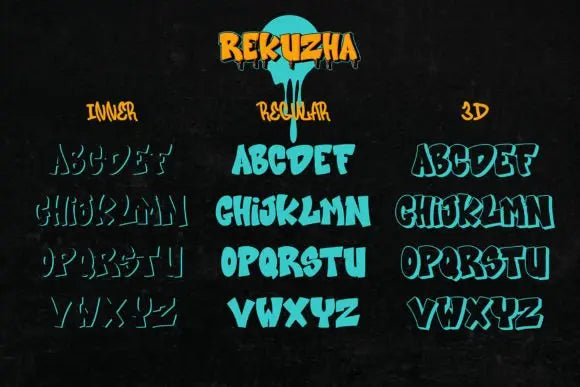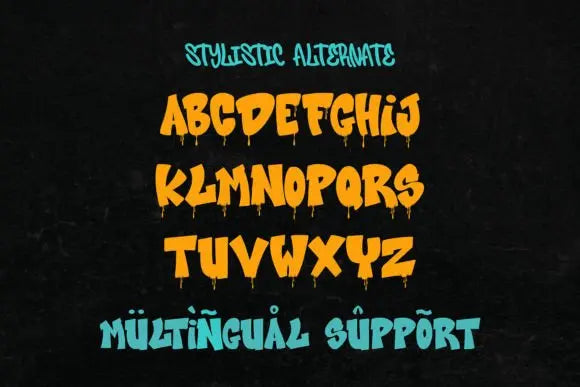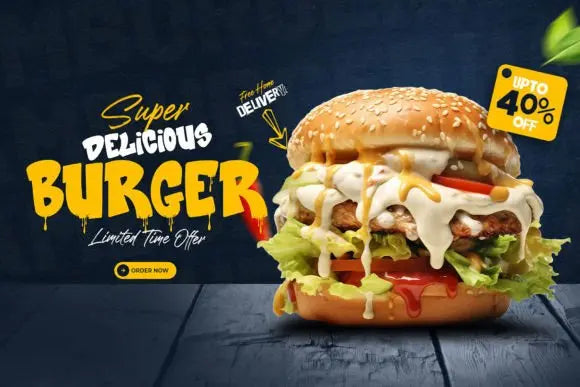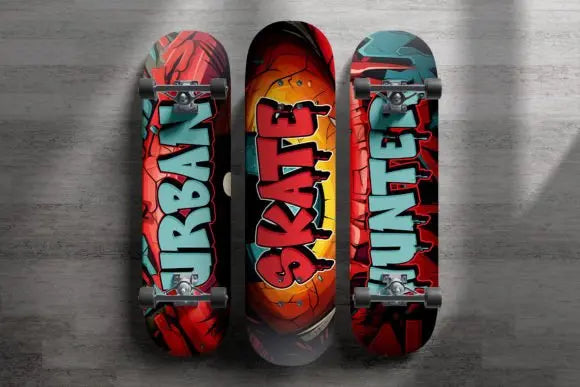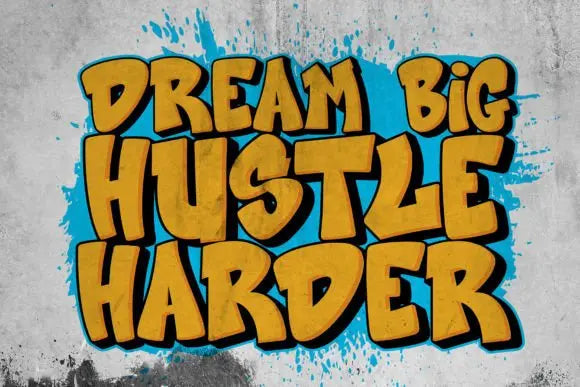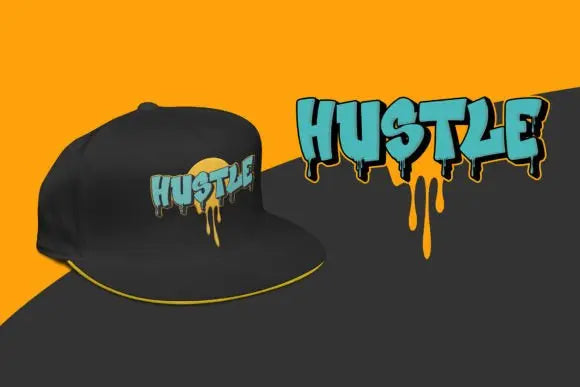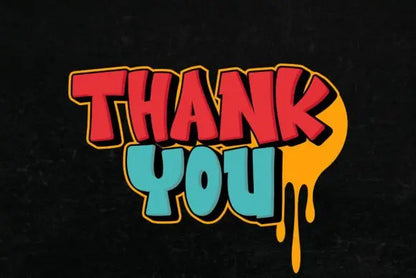
Fuente Rekuzha
Sumérgete en un mundo de audacia, intensidad y creatividad con "Rekuzha", una fuente de graffiti en capas en 3D. Esta fuente, que exhibe formas de letras audaces y enérgicas, está registrada con trazos gruesos y significativos que generan un impacto visual indomable.
El aspecto en capas de “Rekuzha” es el corazón de la aventura: experimenta combinando diferentes estilos, liberando tu espíritu innovador y forjando profundidad en tus diseños. Sus personajes robustos y su composición escalonada hacen de “Rekuzha” la opción perfecta para proyectos que exigen una tipografía llamativa y llamativa: piense en carteles, titulares o diseños centrados en lo urbano.
La tridimensionalidad de esta fuente logra profundidad y compromiso visual, lo que convierte a "Rekuzha" en una opción versátil y dinámica para múltiples exploraciones de diseño gráfico.